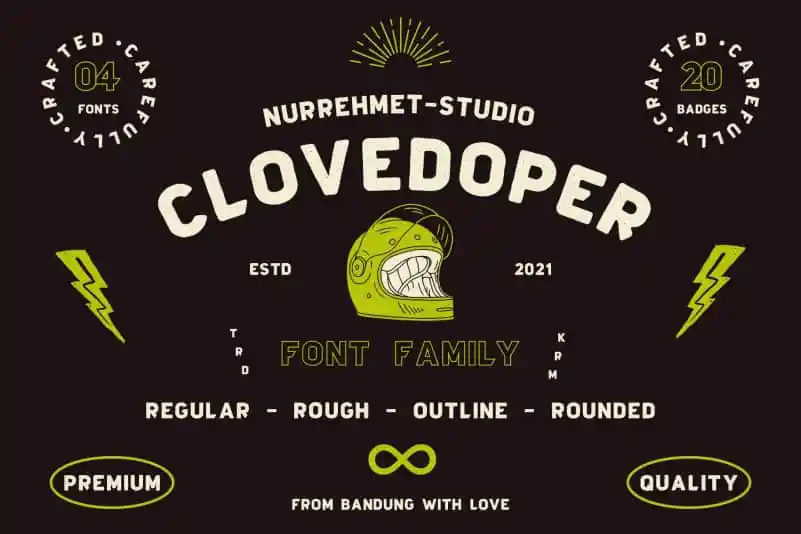
Clovedoper Display Font – Fonte Grátis
Clovedoper Display Font
A Clovedoper Display Font é uma fonte de sans serif ideal para design visual chamativo. Desenvolvida com cuidado por mãos humanas, esta tipografia mistura de forma moderna elementos do estilo das fontes e pacotes de modelo + brastel, destinada a combinar perfeitamente com as pessoas ligadas à motocicleta ou clubes motoristas, assim como com o segmento de lojas customizadoras. Perfeita para ambientes onde deseja destacar seu identidade visual em uma maneira moderna e inovadora, este tipo de fonte é um excelente complemento para qualquer projeto que esteja buscando um toque único e contemporâneo.